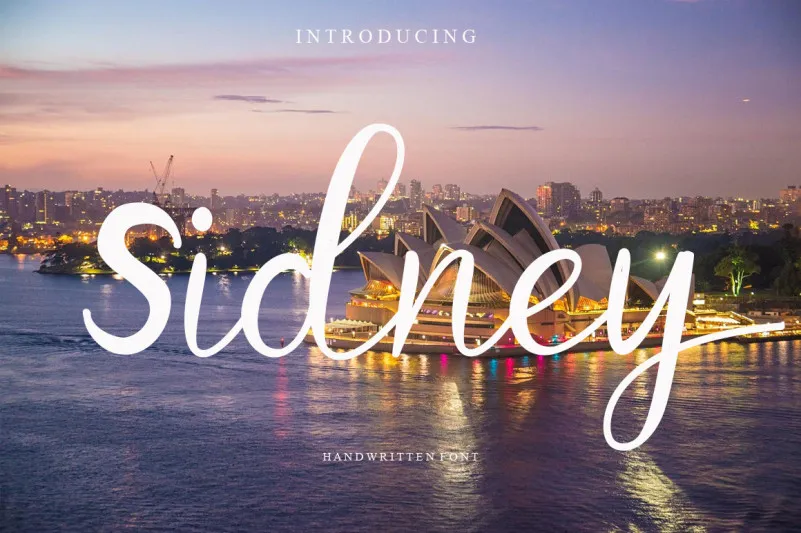
Esta é uma fonte escrita à mão cursiva e fina, carregada de delicadeza y simpatia. É perfeita para quem busca dar um toque agradável e romântico aos projetos gráficos. Com sua textura suave e linhas elegantes, esta fonte ‘Sidney’ enriquece qualquer layout com um aspecto natural e autêntico, tornando-a uma escolha ideal para aqueles que buscam agregar um toque agradável em suas criações de design. A fonte ‘Sidney’ é perfeita para se combinar com texturas delicadas, estilos minimalistas ou até mesmo desenhos enigmáticos, garantindo seu uso em uma variedade incrível de ideias criativas. Essa fonte leva à uma atmosfera descontraída e encantadora, fazendo dela uma excelente opção para qualquer designer que procura adicionar um toque romântico e elegante a seus trabalhos.